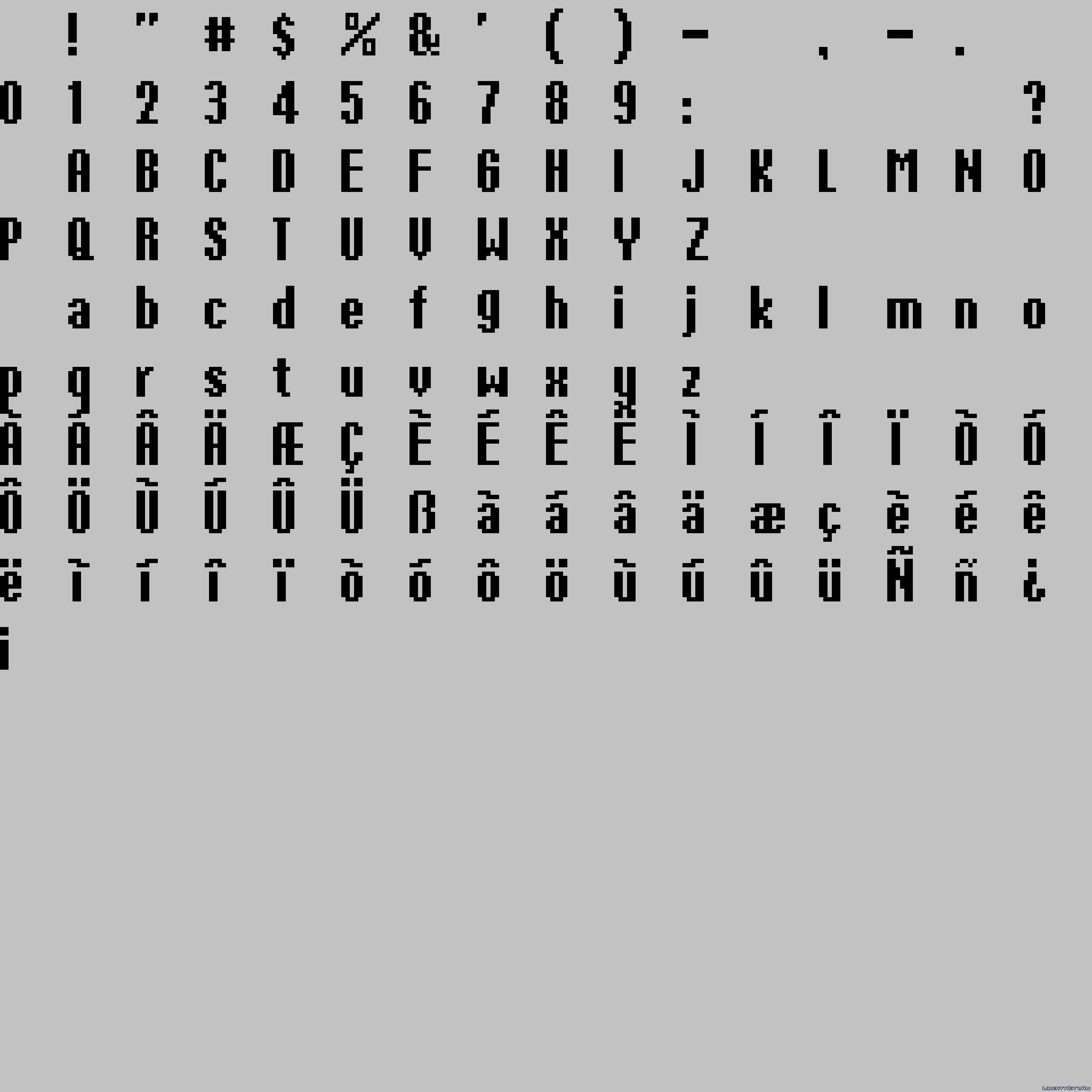
4K Fonts for Grand Theft Auto III
4K Fonts for Grand Theft Auto III by DJDARKO
Это высококачественные (4096px) шрифты для ПК-версии Grand Theft Auto III.
Шрифты были созданы с максимально возможной схожестью с оригинальными и подогнаны под наилучший вид в игре.
ВНИМАНИЕ: Ориентирован под работу с Английским, Испанским, Французским, Итальянским и Немецкими языками!!!